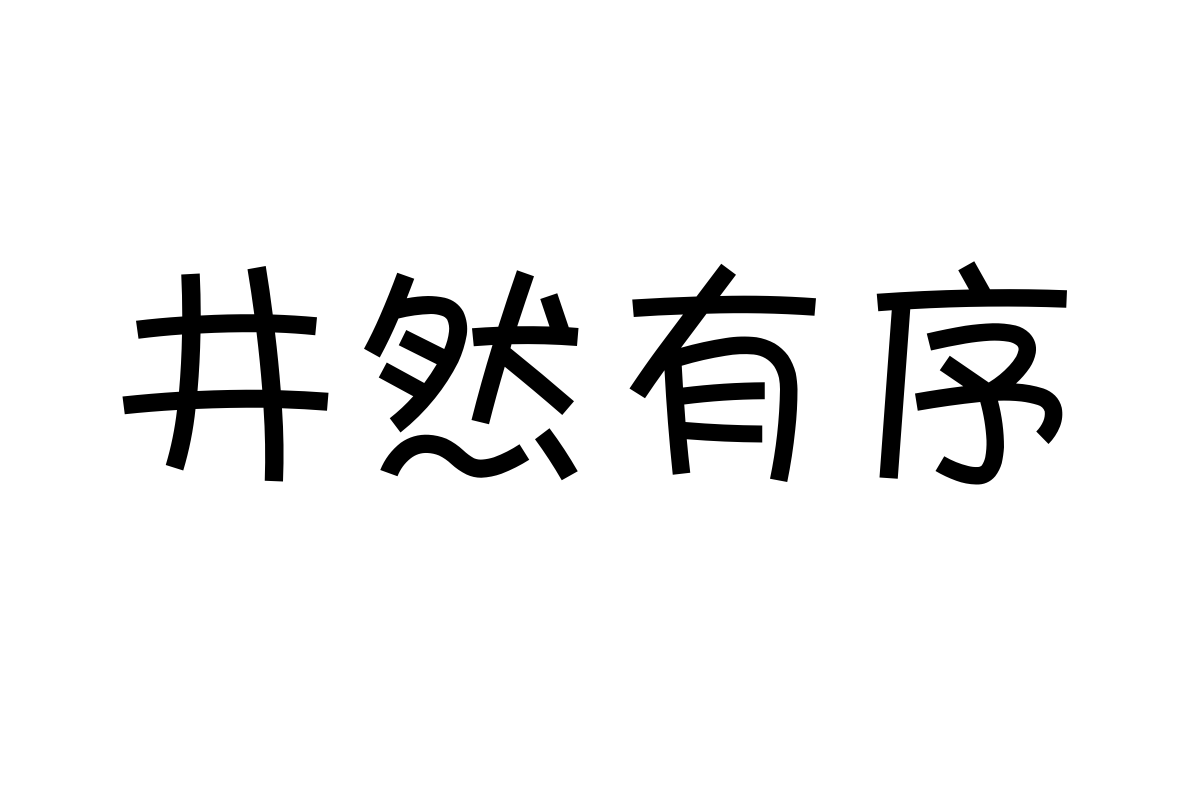
汉仪夏日体简是一款现代简约风格的中文字体,具有独特的艺术感和设计感。它由汉仪字库出品,适用于各种商业和设计场景。这款字体的笔画流畅自然,结构清晰简洁,给人一种轻松愉悦的感觉。同时,它的线条粗细适中,既不会过于粗犷,也不会过于纤细,适合用于标题、正文等多种文本内容。此外,汉仪夏日体简还具有一定的艺术气息,能够提升文本的美感和吸引力。总之,汉仪夏日体简是一款非常实用的现代简约中文字体,适合用于各类商业和设计场景。